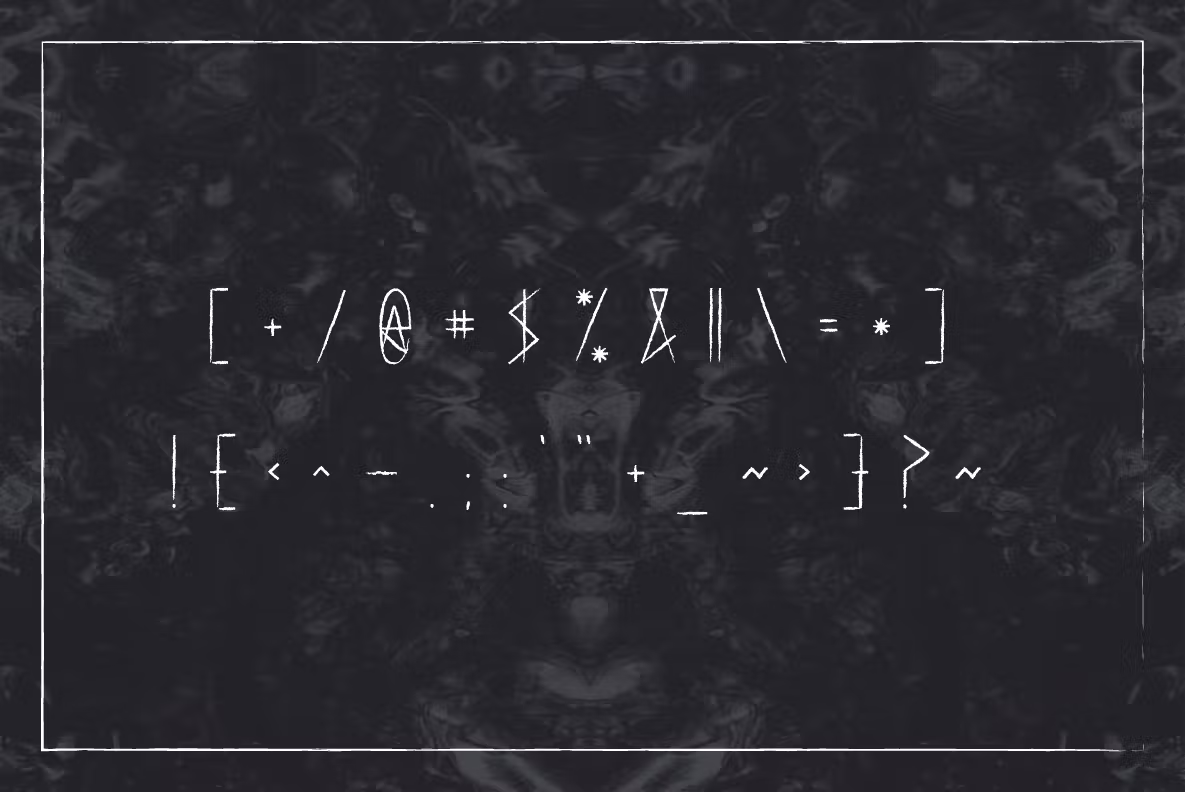
Haext Regular Font
Description de Haext Regular Font
Haext est un Art nouveau rustique néo-gothique, en partie artisan de runes, cette police exprime quelque chose de différent selon la façon dont elle est appliquée : associez-la au noir et blanc ou à la couleur. La police est vendue sous forme de fichier OTF.